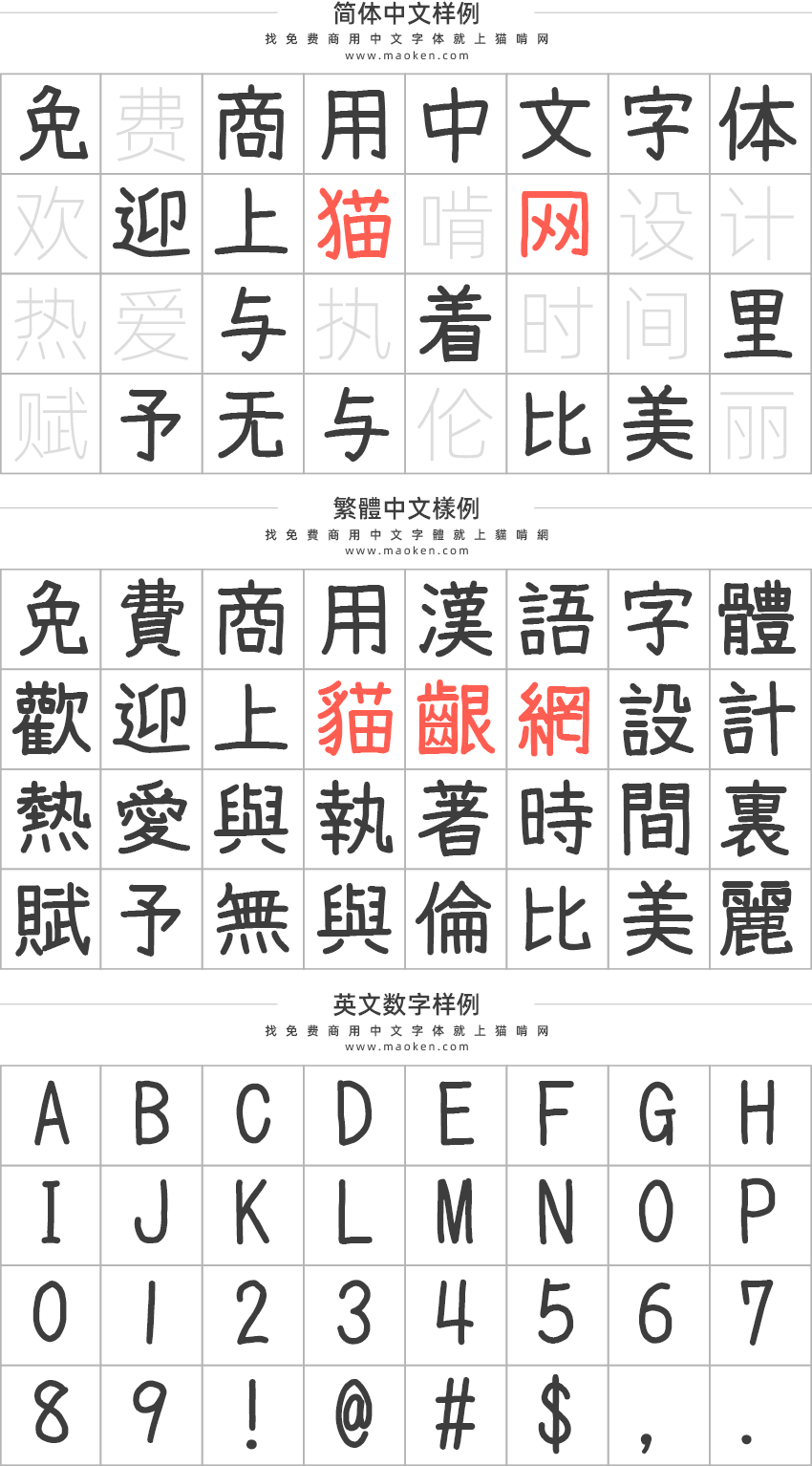
KGothic手写体:日本K先生用钢笔书写的字体免费商用
字体名称:KGothic手写体(日文名:Kゴシック)PS中字体名称:Kゴシック Regular
这是日本的K先生制作的免费商用手写字体。每一个字体都是他在钢笔上书写并精心制作的等宽字体。虽然这是一款日本的字体,但是其收录了日本JIS水准第一至第四水准,所以包含了13500个汉字。但是绝大部分是繁体字,所以如果用简体打不出来的字,可以切换用繁体试一下。因为是精心写字体,所以在各种各样的场合都能灵活使用。